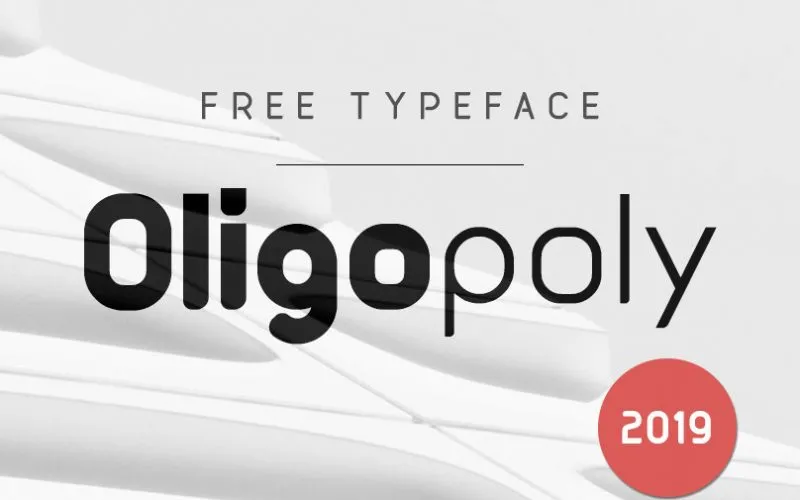
Oligopoly Typeface
Agradecemos pela atenção a esta fonte. É nossa honra apresentar Oligopoly Free Font! Esta tipografia sans-serif, com formas desprendidas e letras não convencionais, cria um impacto visual poderoso mesmo nas dimensões menores. Suas ângulos redondos e terminações suaves não só proporcionam uma aparência agradável, mas também transmitem calor e amizade. Inspirada no amor pelo pequeno detalhe e na equilibrada harmonia que se busca em nossos dias, Oligopoly oferece um design simplesmente singular. Ideal para aplicativos digitais modernos e projetos de identidade visual que buscam uma aparição elegante e atemporal.